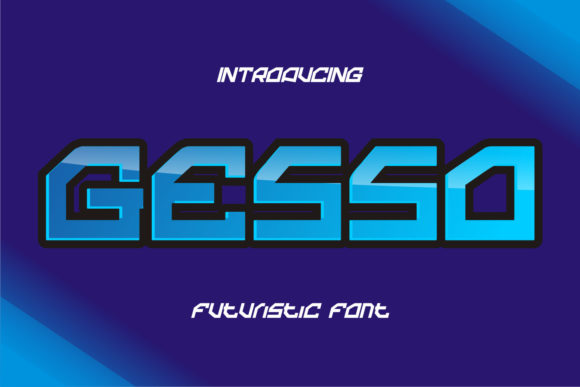
Creativefabrica Gesso Font 2021
[Creativefabrica] Gesso Font (2021)
Gesso - это крутой и техногенный дисплейный шрифт.
Этот шрифт идеально подходит для написания веб-дизайнов, визитных карточек и всего остального, что требует футуристического, уникального штриха.